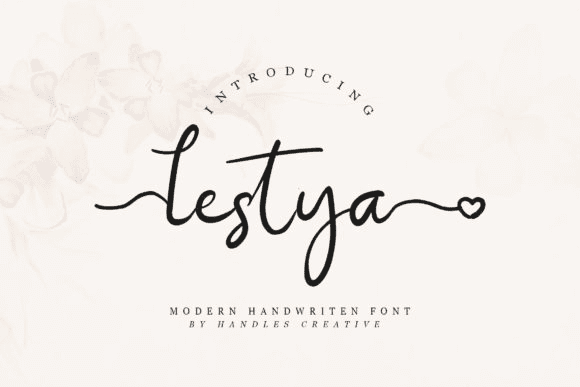
Название: Lestya Font
Lestya - это волшебный скриптовый шрифт, тщательно созданный с оттенком элегантности.
Ищите ли вы шрифты для социальных сетей или каллиграфические шрифты для DIY-проектов, этот шрифт превратит любую творческую идею в настоящее произведение искусства!